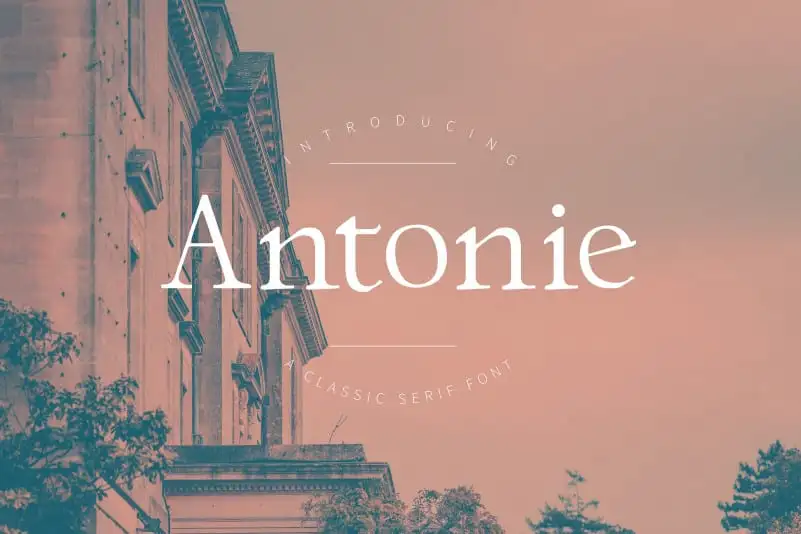
A Antonie Serif Font é uma elegante tipografia serifada que se destaca por sua forma clássica e bold tanto nos tamanhos grandes quanto pequenos. Fabricada pelo designer Type Factory na plataforma 99designs, a Antonie traz um toque vintage em seus alternantes simplificados para estilos de texto. Ideal para aplicativos como logotipos, gráficos, cabeçalhos, outdoors e embalagens, essa fonte minimalista se destaca com uma beleza autêntica. Traz a identidade visual perfeita para marcas e projetos digitais em constante evolução. Inspire-se diariamente com sua imaginação!